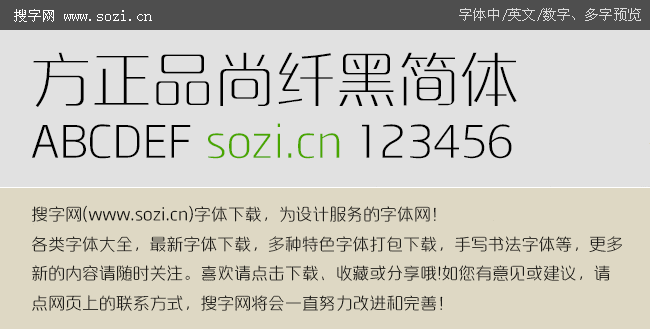
方正品尚纖黑簡(jiǎn)體
搜字網(wǎng)提供一款方正品尚纖黑簡(jiǎn)體中文藝術(shù)字體下載,方正品尚纖黑簡(jiǎn)體是一款由黑體為原形再加工的藝術(shù)字體,,整體效果十分出色,可用于藝術(shù)設(shè)計(jì)、包裝印刷、圖形設(shè)計(jì)等領(lǐng)域。